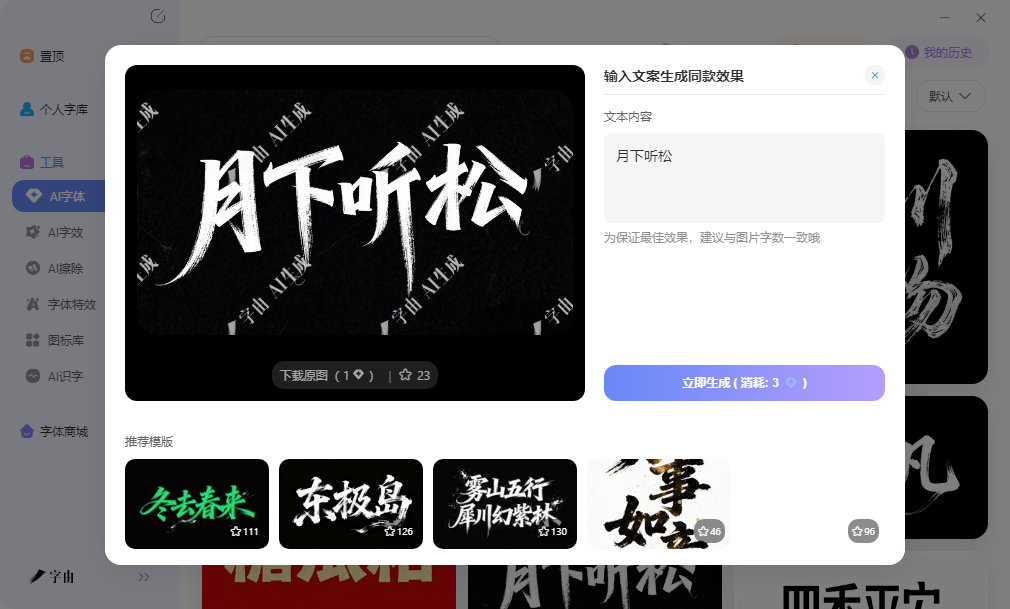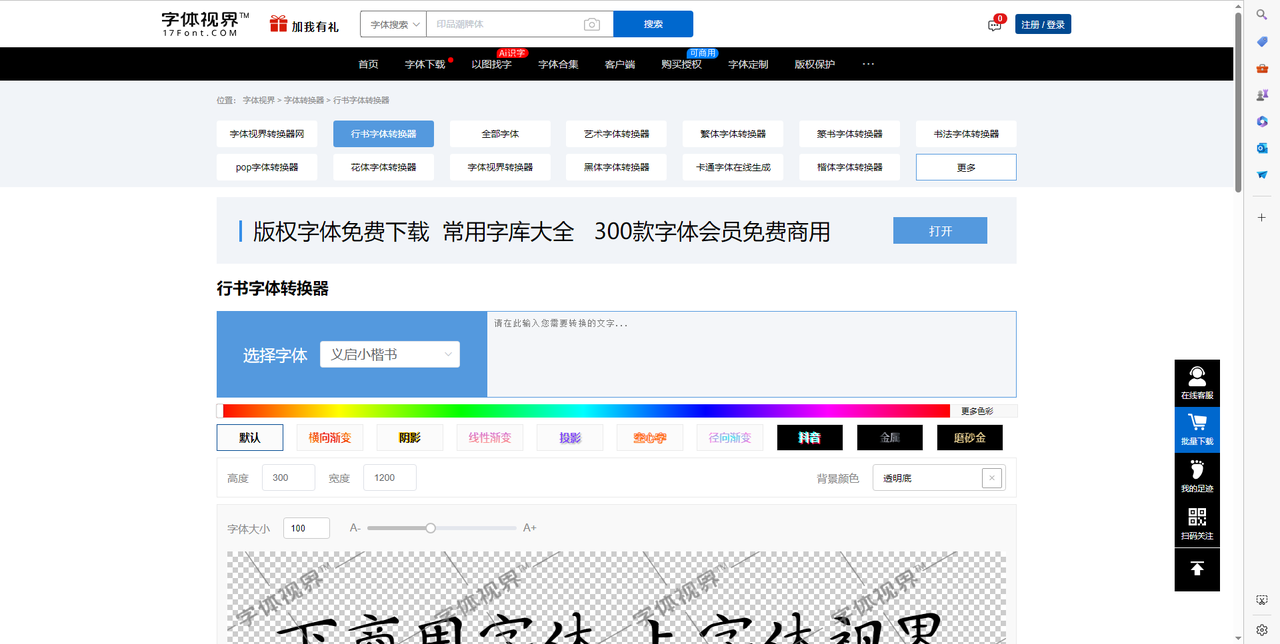
行书字体在线生成器,海报标题和文创设计直接套用
文创店做招牌、茶馆印菜单、活动做海报,经常需要传统书法中的行书字体来营造文化感。一般来说是找书法家手写或者自己在设计软件里用毛笔字库慢慢调描边和飞白,费时费力不说,效果还不一定理想。现在有不少行书字体在线生成器,打开网页输入文字就能直接生成带行书韵味的文字效果,下载就能用。这篇文章整理了几个实用平台,从系统管理到单一生成都有涉及,帮你快速拿到适合海报标题和文创设计的行书素材。
字由目前有超过一万款的字体资源,其中不少带有书法韵味的手写体和行书风格字体。对于需要行书字体在线生成器辅助的文创项目和海报设计,字由是分在行。
AI 字效功能是字由应对这类需求的直接工具。在模板库里能找到不少适合文化类项目的行书风格特效,比如模拟毛笔飞白质感的古风题字效果、带有手写连笔韵味的招牌字体样式、以及笔画粗细变化明显的艺术标题效果。这些模板把专业设计软件里的图层样式和混合模式打包成了可直接套用的方案,用户不需要理解投影角度、渐变节点、描边宽度这些专业参数,选中模板输入文字就能生成。操作流程很固定,浏览模板、输入文案、点击生成、下载 PNG 图片,四步完成。
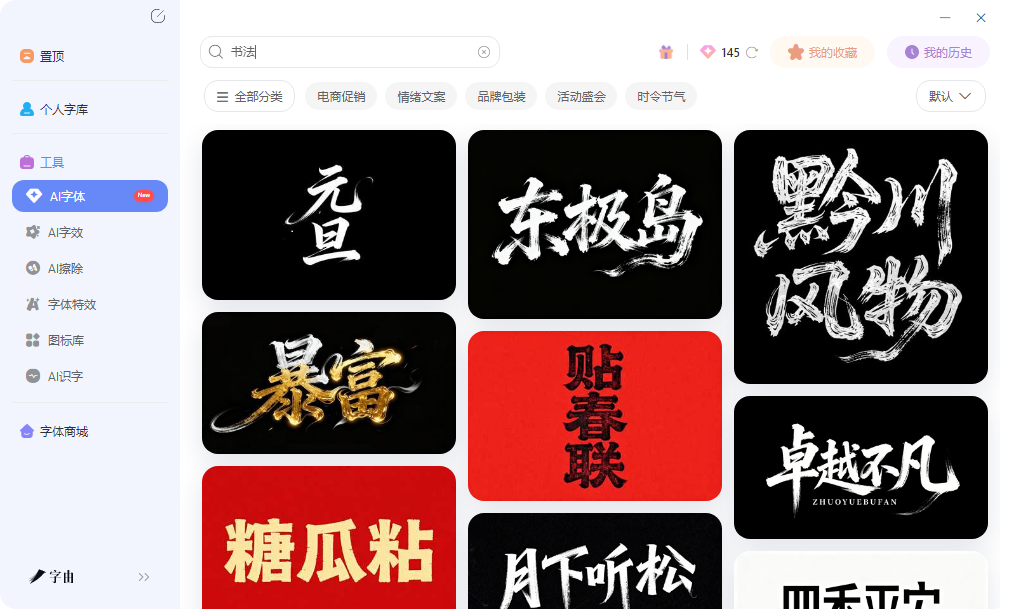
生成的 PNG 图片背景透明,可以直接拖进 Photoshop、Illustrator,也可以放进 PPT 里做标题页,或者印在文创物料上。做茶馆菜单、书店招牌、活动海报、文化展览物料时,这种即拿即用的行书图片能省去大量手工调整时间。批量处理系列物料时,固定同一款行书模板,分别输入不同文案,能产出风格统一的多张文字图,保持视觉一致性。
AI 配字功能则解决选字困难。面对字由庞大的字体库,很多人不知道哪款行书字体更适合当前项目。在 AI 配字里输入古风、手写、文创、招牌等关键词,系统会推荐几款风格匹配的行书字体组合,并给出搭配建议。推荐结果里包含不少标注免费商用标签的字体,比如江西拙楷笔画带有手写不规则感,鸿雷板书简体结构舒展有温度,看到合适的可以直接激活在设计软件里调用。预览框支持输入自己的实际文案,实时看到行书字体在线生成器的排版效果,确认合适再收藏。
2、字体视界
字体视界提供了一个行书字体转换器,是行书字体在线生成器的一种实用形式。在转换器页面输入需要生成的文字,从字体列表中选择行书风格字体,可以实时调整文字颜色、字号、图片高度和宽度等基础参数。平台支持多种视觉特效叠加,包括横向渐变、阴影、线性渐变、投影、空心字、径向渐变、描边、金属质感、磨砂金等效果,这些特效能让生成的行书文字更具视觉冲击力和装饰性。
调整好所有参数后,页面下方会实时显示预览效果,用户可以反复微调直到满意,然后生成最终图片下载保存。对于需要快速获得带复杂特效行书标题的用户来说,这种参数化调整方式比固定模板更灵活,能做出更个性化的效果。平台还提供了 POP 字体转换器、花体字体转换器、艺术字体转换器、黑体字体转换器等相关工具,覆盖多种风格需求,方便用户在同一平台尝试不同风格。
3、书法字典
这个平台专注书法字体在线生成,提供了大量书法名家字体资源,是行书字体在线生成器领域的一个专业选择。用户输入文字后,可以从丰富的字体列表中选择不同的书法字体进行预览,涵盖行书、楷书、草书、隶书等多种书体。平台展示了清晰的书法字体预览效果,用户可以看到不同书法家风格的行书字体在线生成器结果,对比笔画粗细、连笔方式和整体气韵。每款字体都配有查看、生成、下载按钮,操作流程清晰明了。
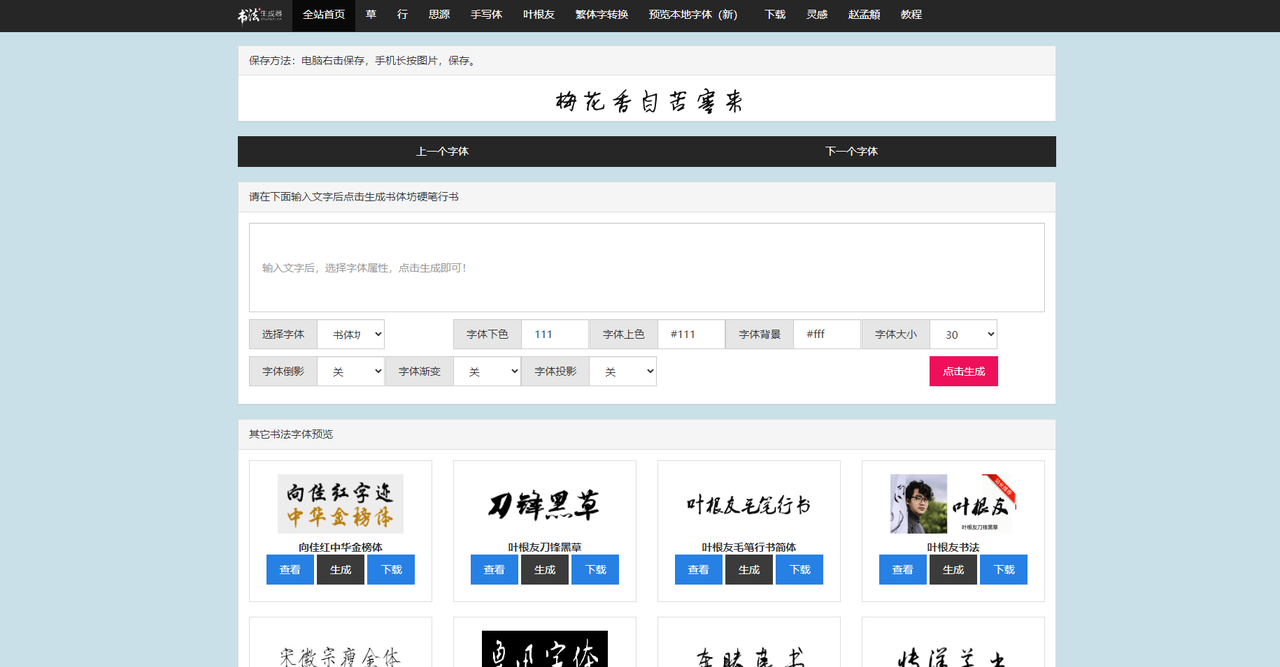
4、千千秀字
千千秀字提供了篆书、隶书、楷书、草书、行书五种主要书体的在线预览和转换工具,是一个综合性的行书字体在线生成器平台。用户输入 5 到 18 个文字,从下拉菜单中选择行书书体,调整文字颜色、字号大小、背景颜色等参数,点击转换按钮即可看到行书效果。转换后的行书字体可以直接在页面预览,支持调整多种显示参数,适合需要文化感文字的文创设计和海报标题制作。平台界面简洁,操作门槛低,不需要注册就能使用基础转换功能。
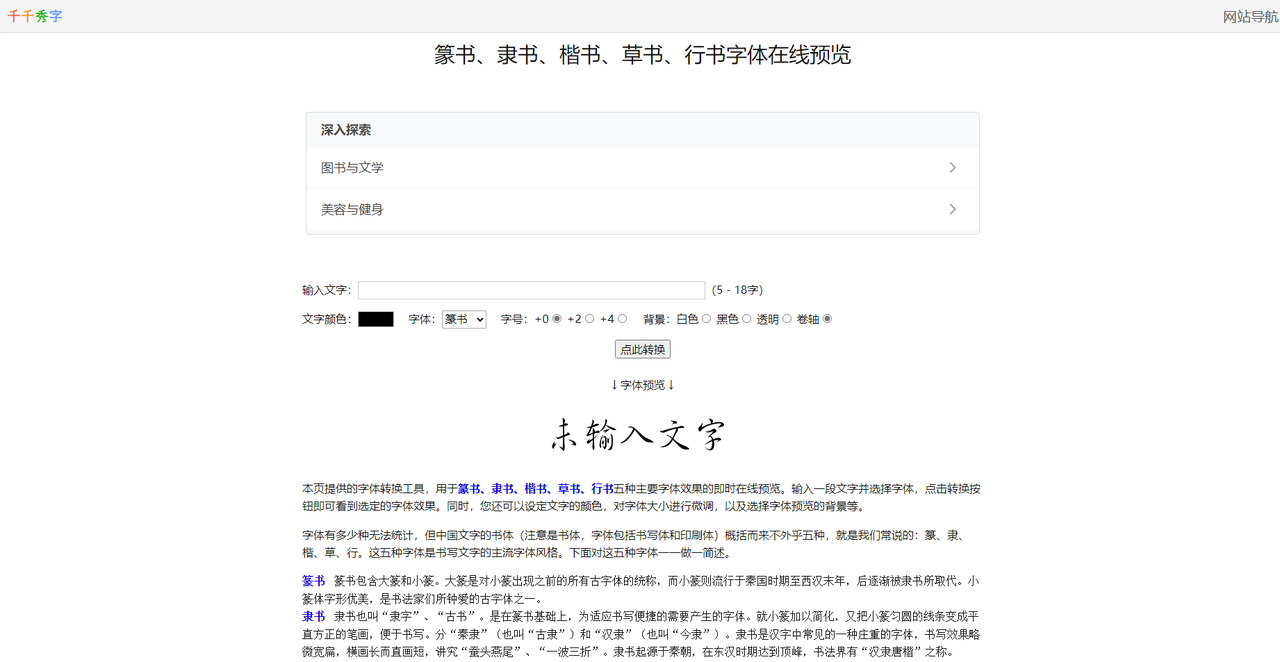
5、第一字体网
第一字体网提供了专门的行书字体转换器在线转换生成功能,是行书字体在线生成器的一个实用选择。首页展示了手写字体在线转换器和奶酪字体在线转换器等热门工具,下方列出了艺术字转换器、在线书法字体生成、篆体转换器、毛笔字在线生成器、钢笔字转换器、美术字体转换等数十种相关工具,覆盖范围很广。在行书字体转换器页面,用户可以选择司马彦行书等具体字体样式,调整字号、行高、字体颜色、背景色、描边等参数,输入文字后在线生成行书预览图。平台支持下载字体文件和生成图片两种输出方式,方便不同使用场景。对于需要批量尝试不同行书风格、或者想在一站式平台找到多种书法相关工具的用户来说,第一字体网提供的多样化转换器可以一次性满足多样需求,省去了在多个网站之间切换的麻烦。